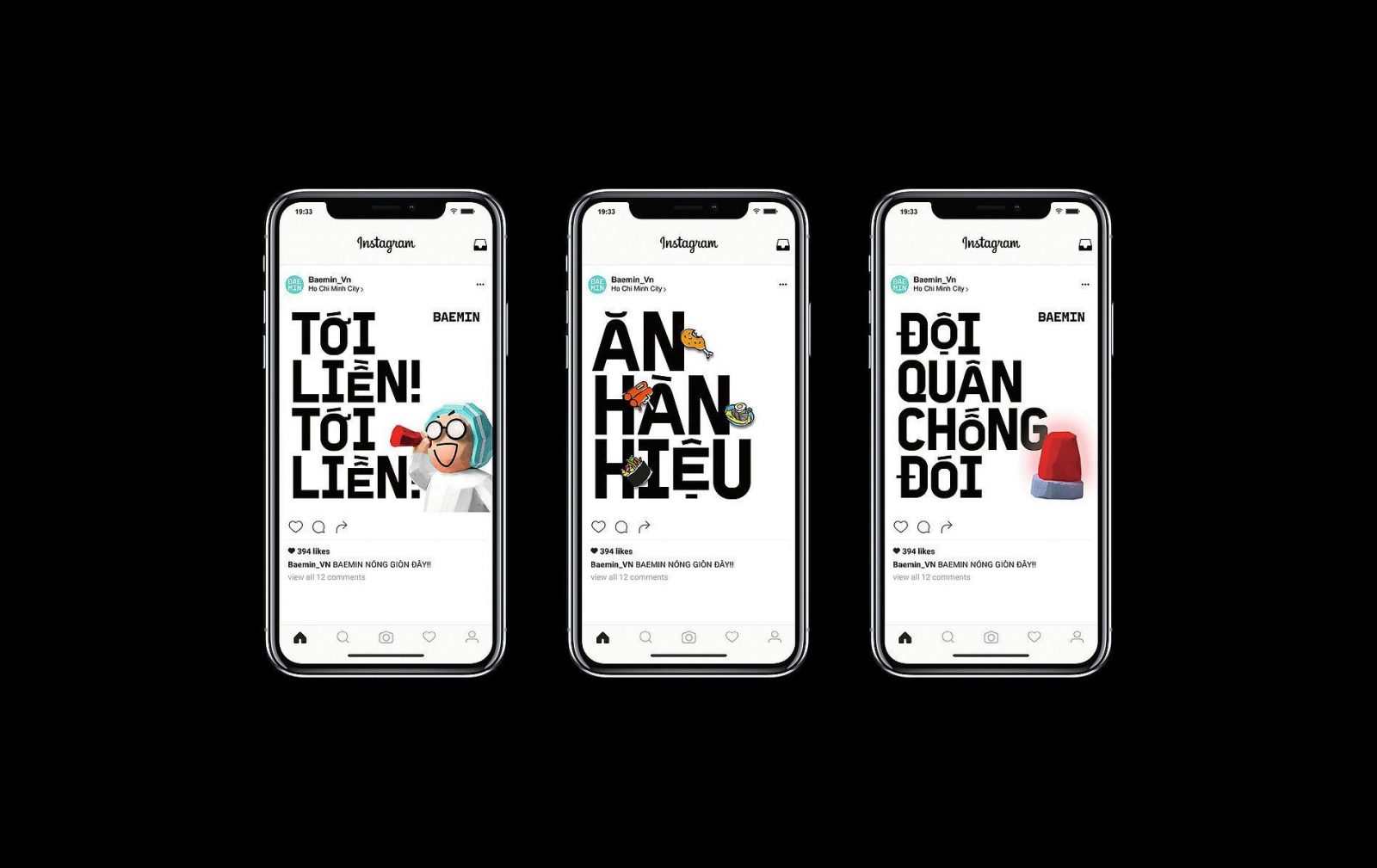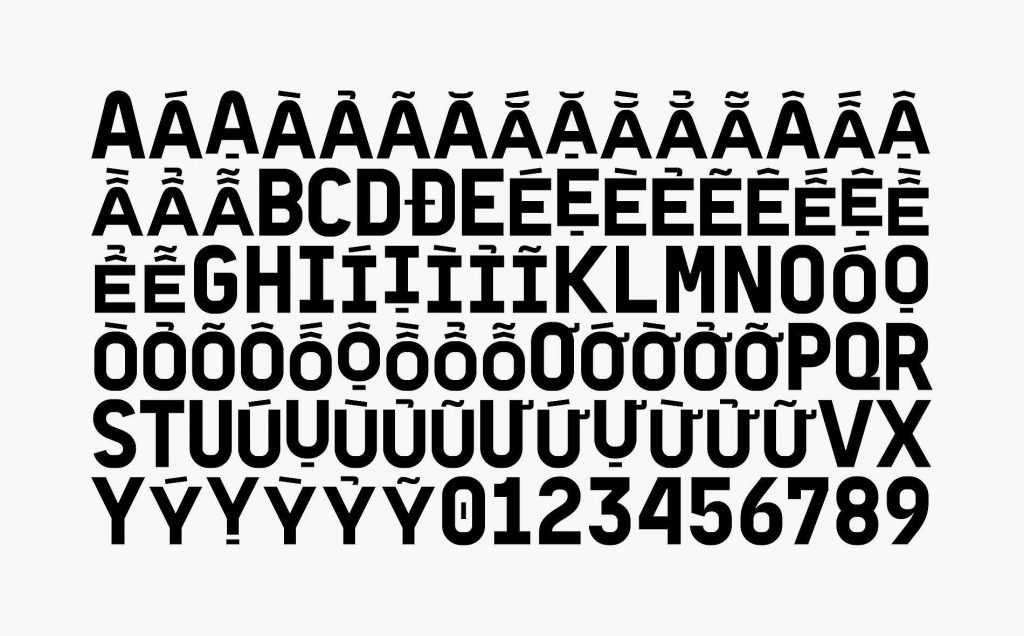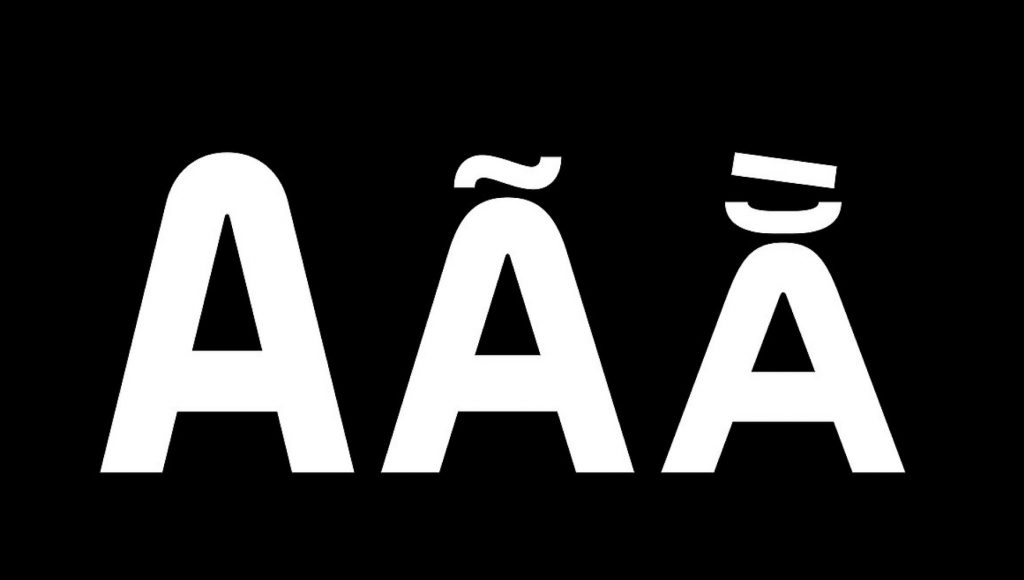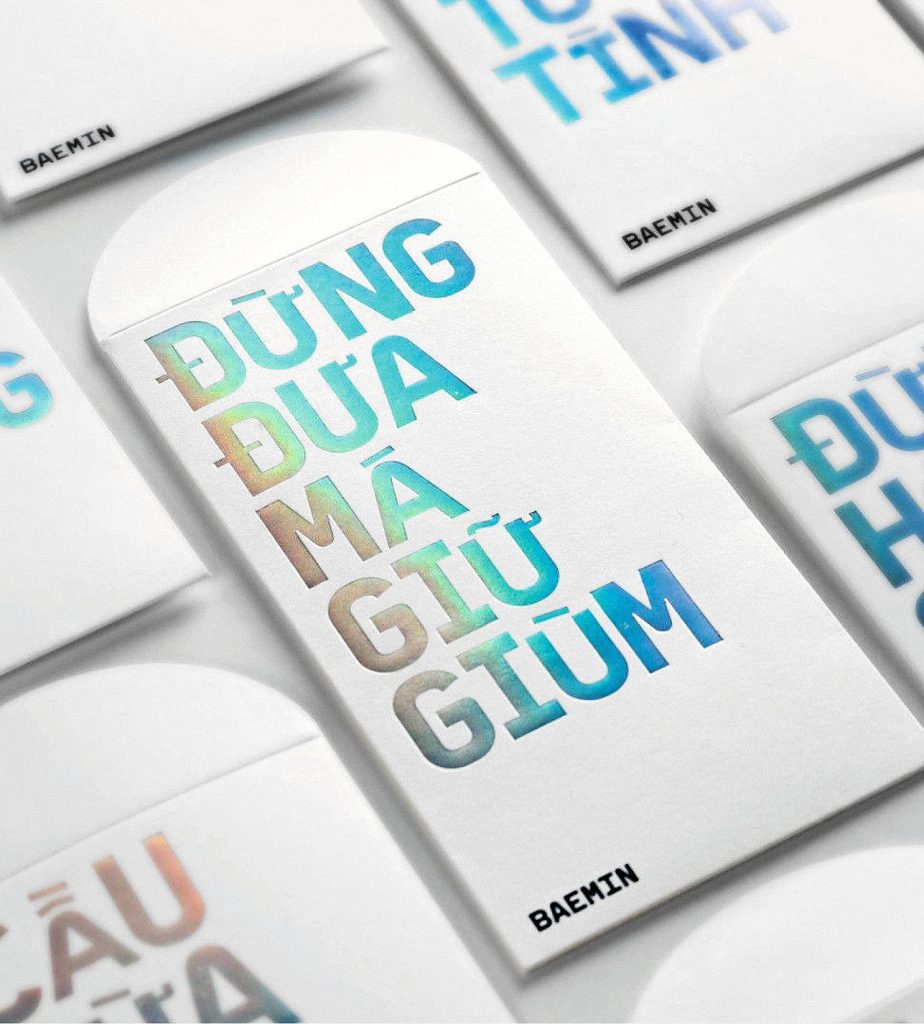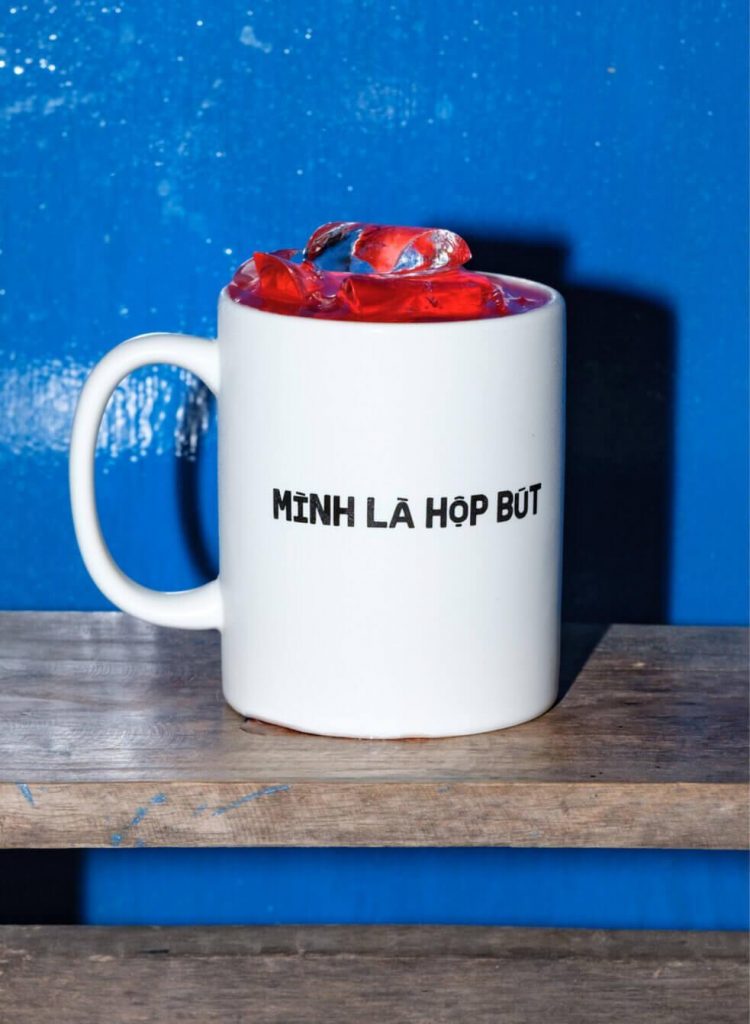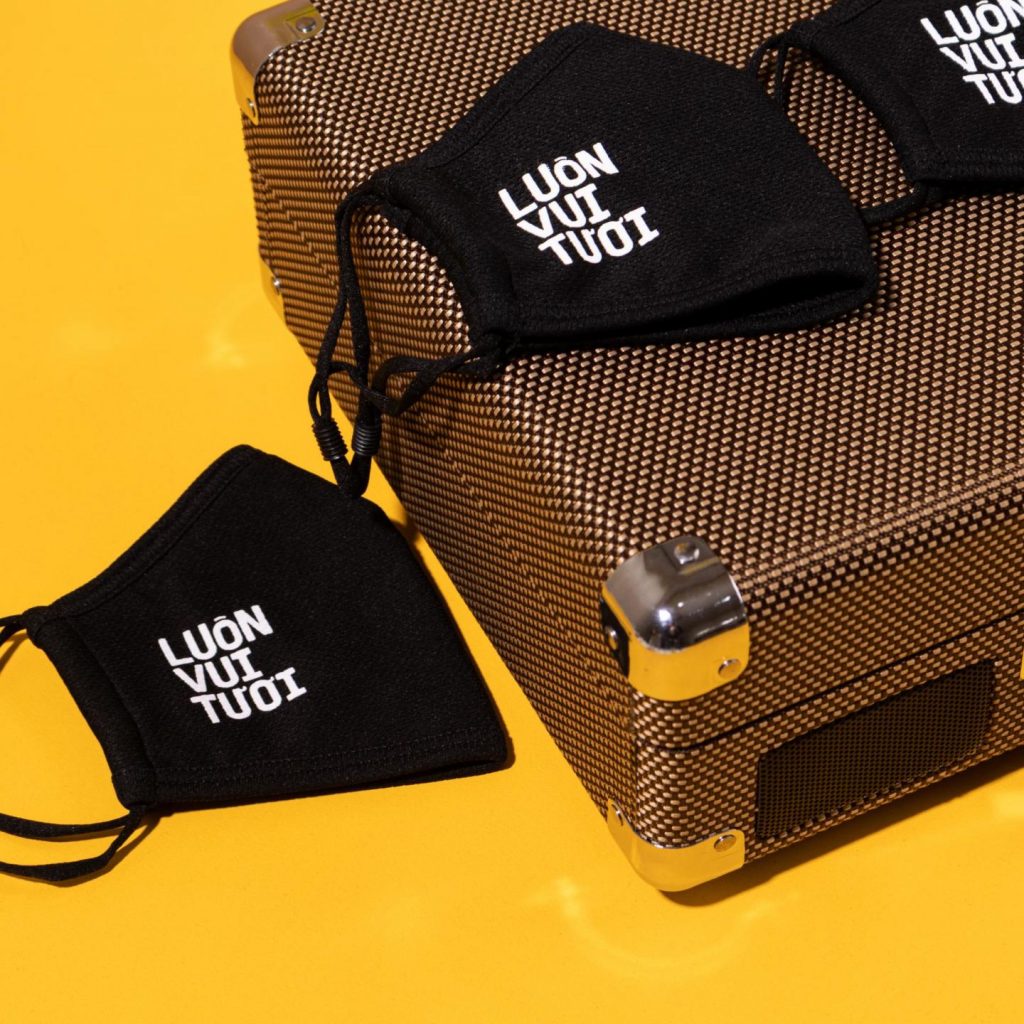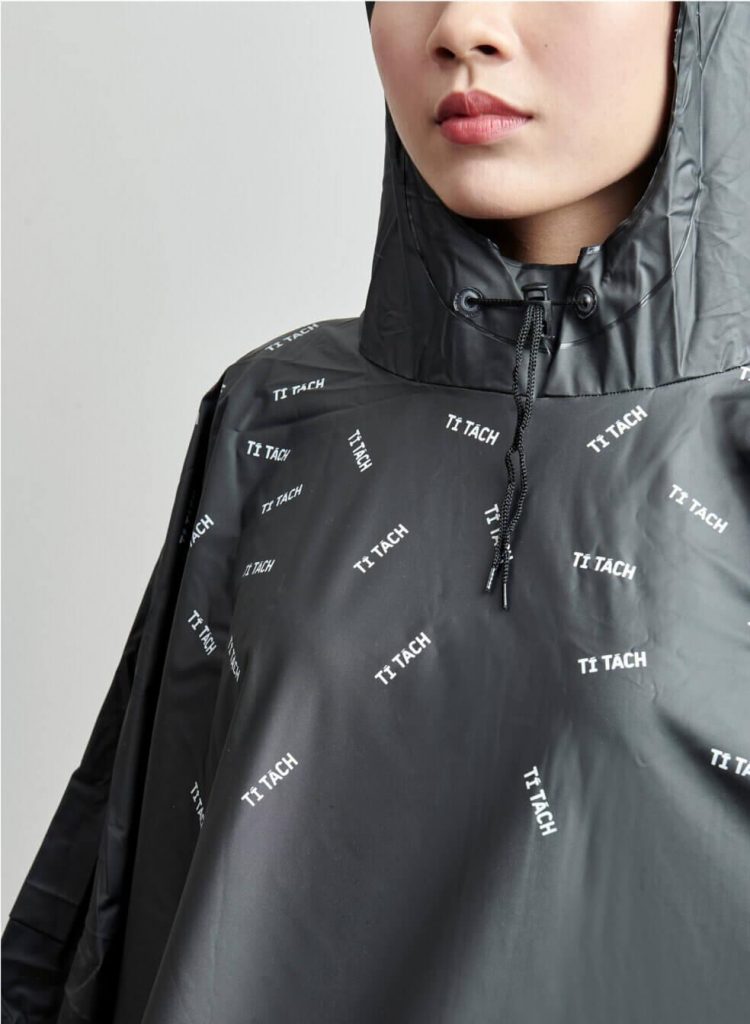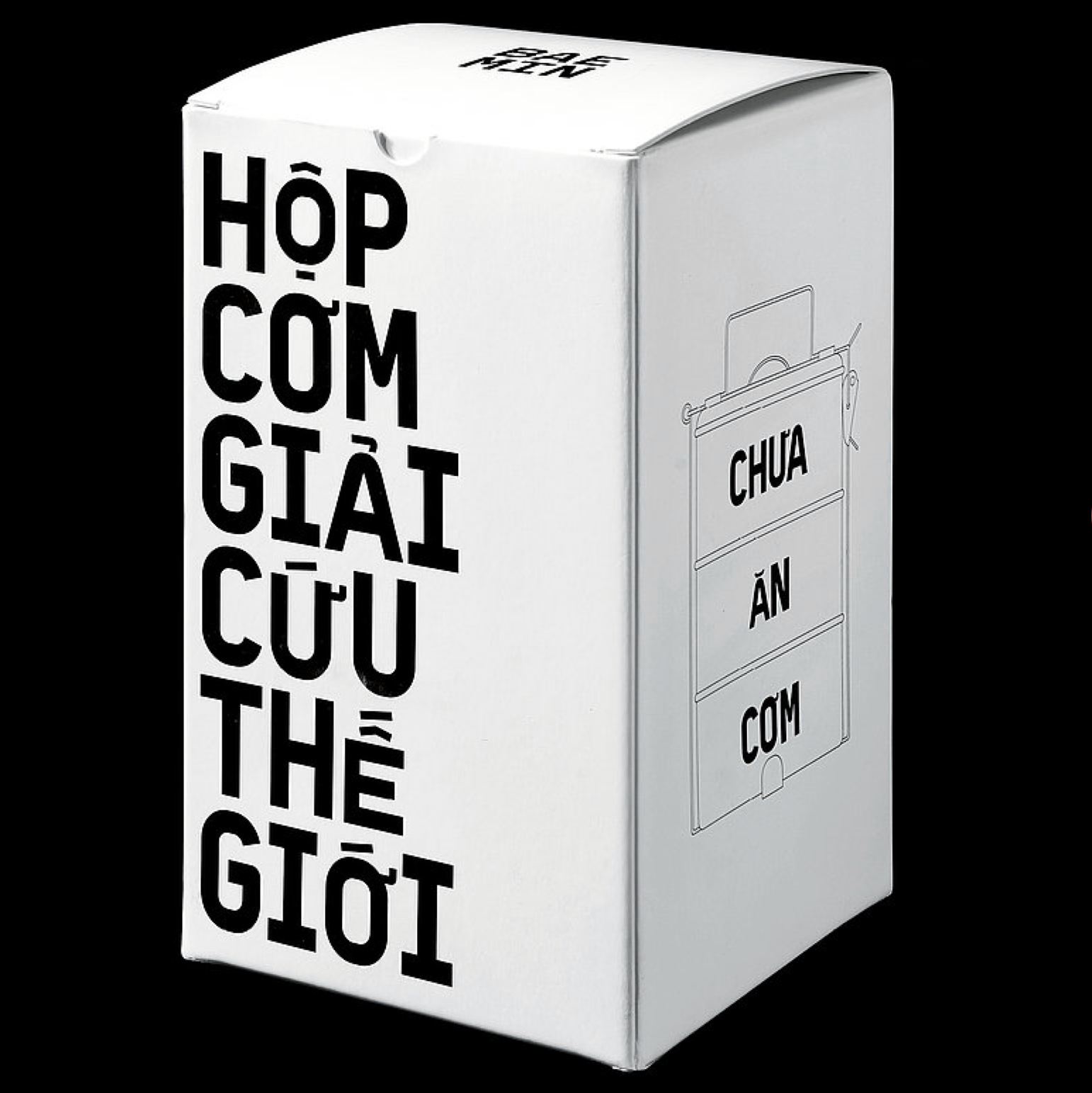
Vừa qua, bộ phông chữ BM Daniel mà BAEMIN thiết kế riêng cho thị trường Việt Nam đã thắng giải thưởng cao nhất tại Lễ trao giải Red Dot Awards 2021. Sau giải thưởng tại Type Champion Awards năm 2020, phông chữ BAEMIN tiếp tục được vinh danh trong giải thưởng thiết kế danh giá.
Lấy cảm hứng từ cách thức xây dựng thương hiệu thành công của BAEMIN tại Hàn Quốc, ứng dụng giao thức ăn BAEMIN đã phát triển và giới thiệu bộ phông chữ dành riêng cho thị trường Việt Nam mang tên BM Daniel. Bộ phông chữ này được BAEMIN và Rice Creative sáng tạo thông qua những quan sát và tìm hiểu về thị trường sở tại cũng như những nét đặc trưng trong văn hóa ẩm thực đường phố Việt Nam.
Đặc điểm của BM Daniel là “ép” các dấu, mũ của các chữ vào một chiều cao giới hạn sẵn khiến cho dòng chữ trở nên sinh động và có hồn, tạo cảm giác gần gũi với những nội dung dí dỏm được truyền tải.
Trong tháng 11 vừa qua, bộ phông chữ BM Daniel đã giành được giải thưởng cao nhất “Best of the Best” ở hạng mục Thương hiệu và Thiết kế Truyền thông tại Lễ trao giải Red Dot Awards 2021. Đây được coi là một trong ba giải thưởng thiết kế lớn của thế giới bên cạnh iF và IDEA Design Awards nhằm tôn vinh những sản phẩm sáng tạo nghệ thuật xuất sắc nhất.
BM Daniel được đánh giá đã thể hiện một cách lôi cuốn, dí dỏm và sáng tạo bảng chữ cái tiếng Việt, một thử thách vốn được xem là rất khó cho các nhà thiết kế bởi sự phức tạp của các dấu thanh. Để dành được chiến thắng này, BM Daniel đã đạt được những điểm số cao nhất cho các tiêu chí như ý tưởng, hình dáng thiết kế và tác động nhận diện thương hiệu. Ban giám khảo cho giải thưởng này bao gồm 24 chuyên gia thiết kế, truyền thông hàng đầu đến từ khắp nơi trên thế giới.
Ông Kiwan Ihn – Tổng Giám đốc của Woowa Brothers Việt Nam chia sẻ: “BM Daniel đóng vai trò quan trọng trong việc tiếp cận người dùng Việt Nam ngay từ những ngày đầu tiên ứng dụng ra mắt. Tại BAEMIN, chúng tôi chú trọng đến cảm xúc của người dùng và không ngừng đưa ra các ý tưởng và sản phẩm sáng tạo để nâng niu và chia sẻ những cảm xúc ấy. Việc thiết kế và áp dụng những bộ phông chữ riêng đã được đón nhận tích cực tại Hàn Quốc, chúng tôi hy vọng có thể sử dụng cách tiếp cận này để góp phần kể những câu chuyện độc đáo và thú vị của nền ẩm thực Việt Nam và kết nối những người tham gia hệ sinh thái công nghệ ẩm thực (food tech) với nhau.”
Người dùng có thể dễ dàng bắt gặp bộ phông chữ BM Daniel ngay trong ứng dụng BAEMIN, trên các bảng quảng cáo ngoài trời hay tại các ấn phẩm truyền thông khác. Bộ phông chữ này cũng được sử dụng trên đồng phục của các đối tác tài xế hay in trên các logo BAEMIN đặt tại các đối tác nhà hàng.
Ngoài ra, ứng dụng BAEMIN cũng sản xuất những món văn phòng phẩm quen thuộc cộp mác BAEMIN Studio với các tên gọi dí dỏm được in bằng phông chữ BM Daniel như Túi Ba Gang, Ly Hộp Bút, Khẩu Trang Luôn Vui Vẻ, Thẻ Quà Tặng hay Áo Mưa Tí Tách. Tất cả đều nhận được sự yêu mến và đón nhận tích cực từ người dùng BAEMIN.